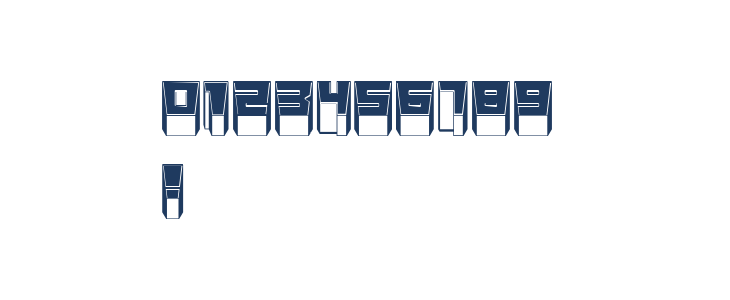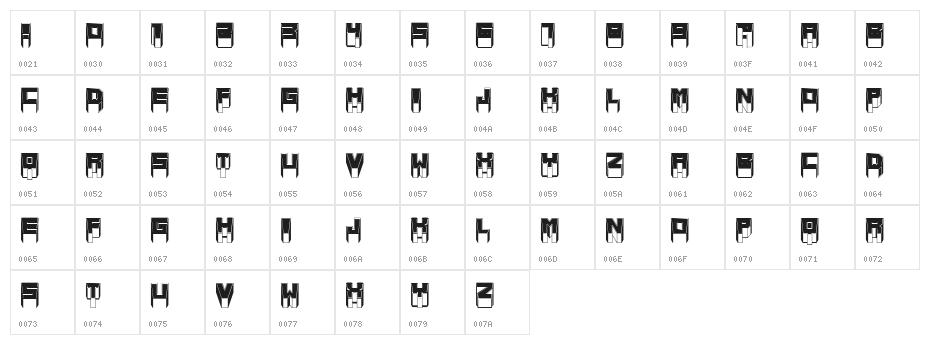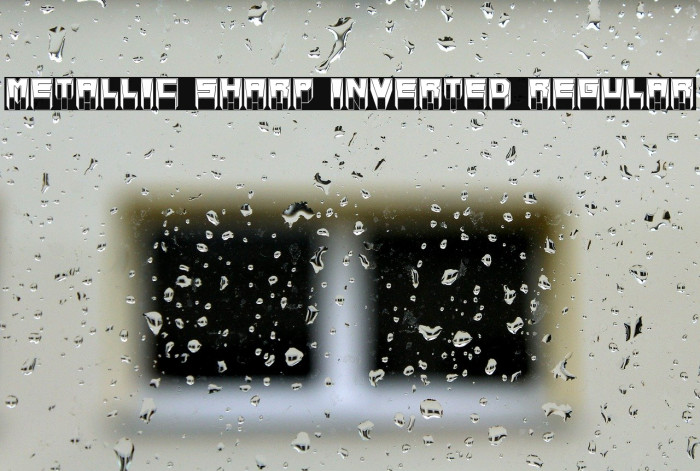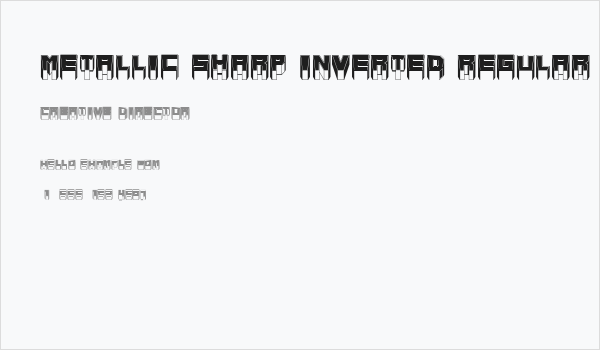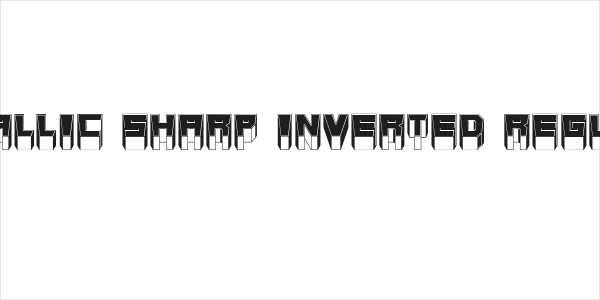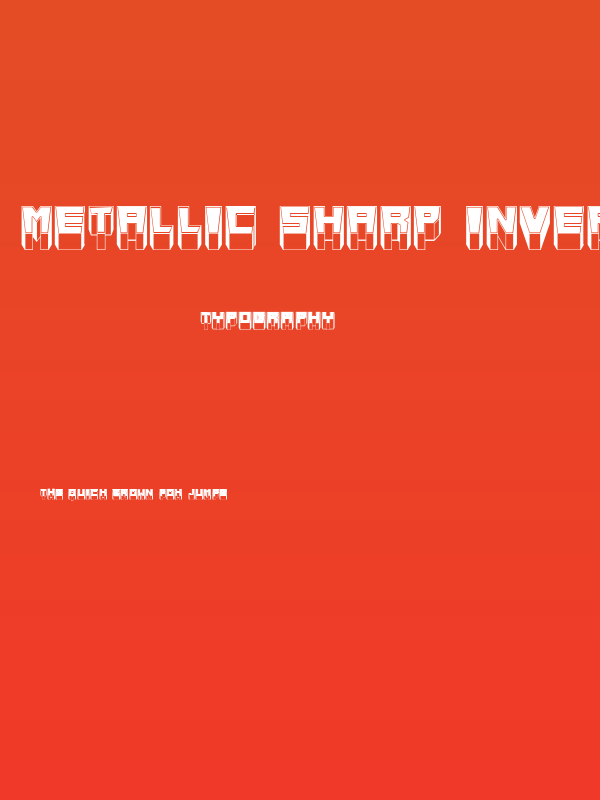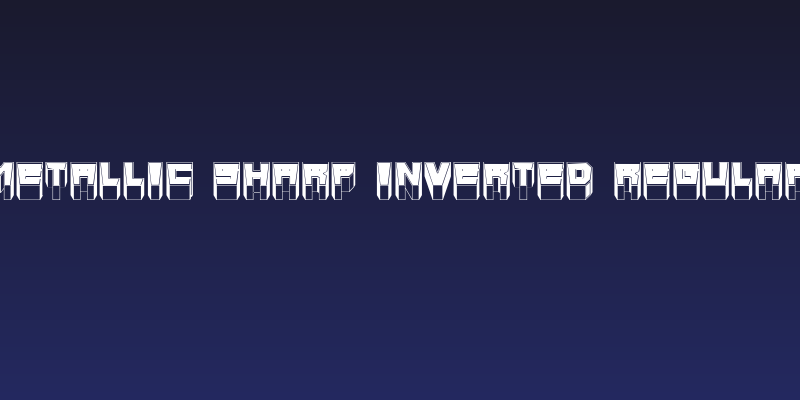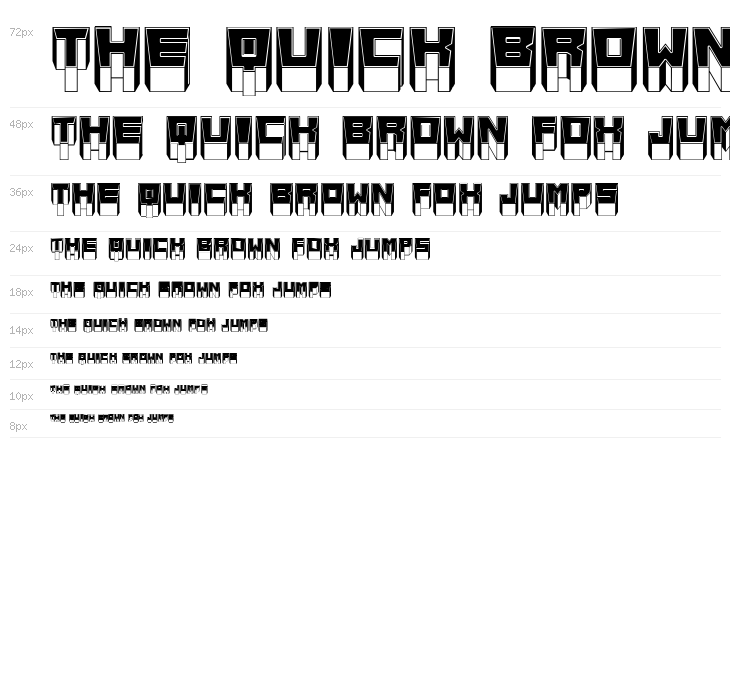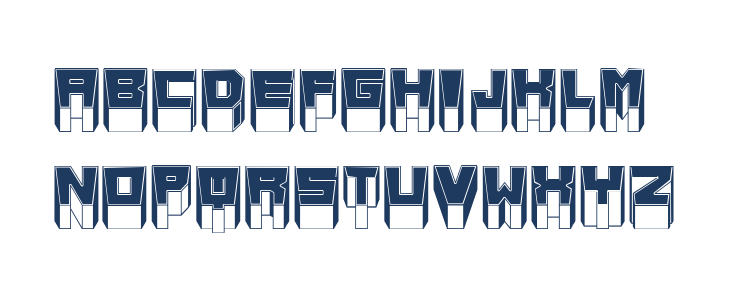
Metallic Sharp Inverted Regular Font
| Progetti proposti | Ideal for use in branding, logos, posters, video game graphics, and any project needing a futuristic or industrial aesthetic. |